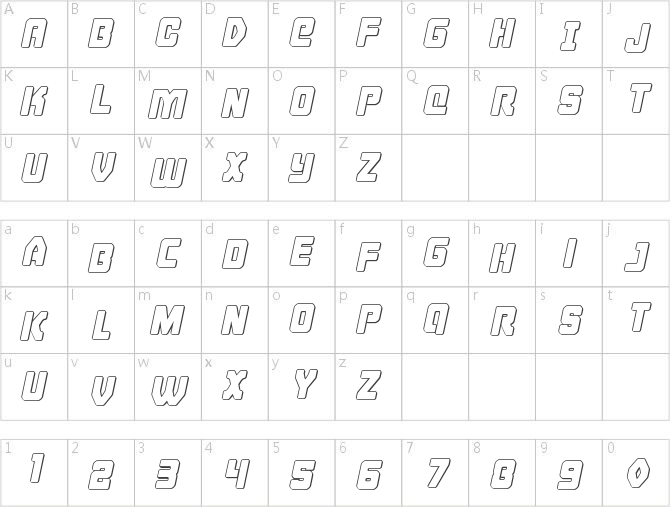
字體名稱: Cyborg
Cyborg Rooster Outline Italic
Cyborg Rooster Outline Italic介紹
Cyborg Rooster Outline Italic字體字庫是一款讓人賞心悅目、百看不厭的英文字體,適合各類廣告和產品包裝設計應用,字體大小0.08MB,格式為ttf字體,上傳用戶是文生電腦,作者/版權方為未知